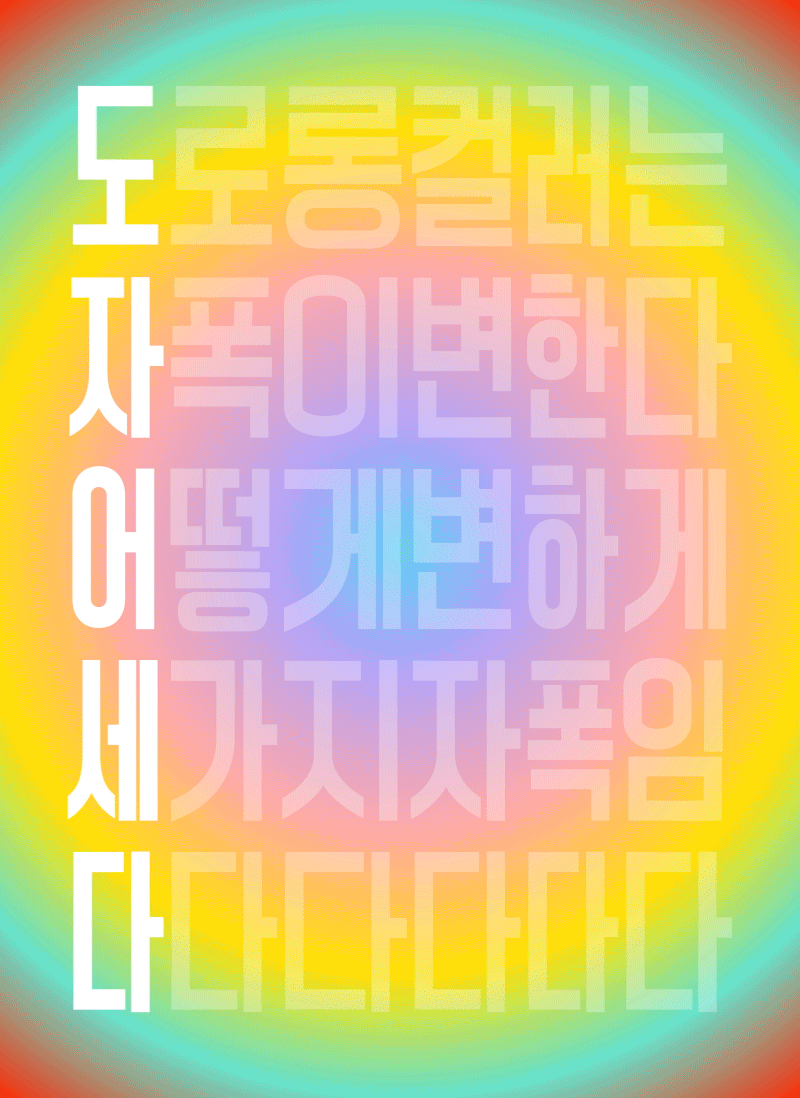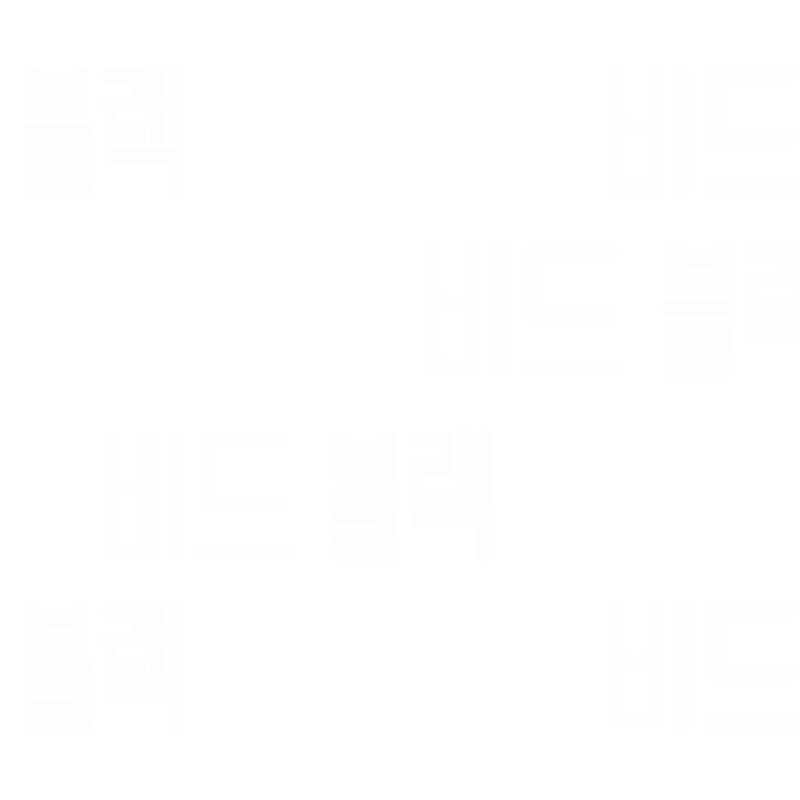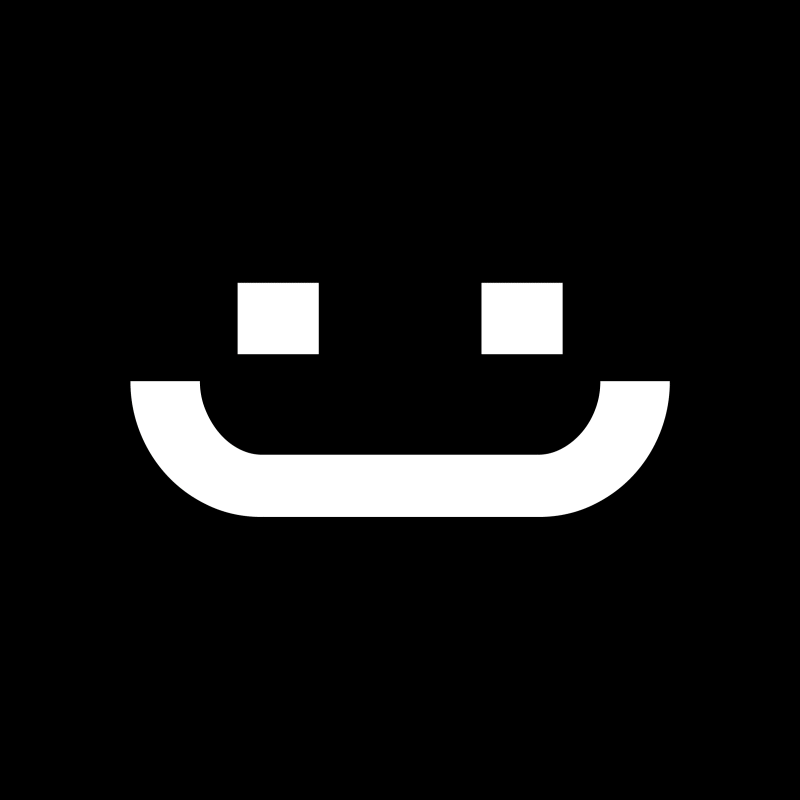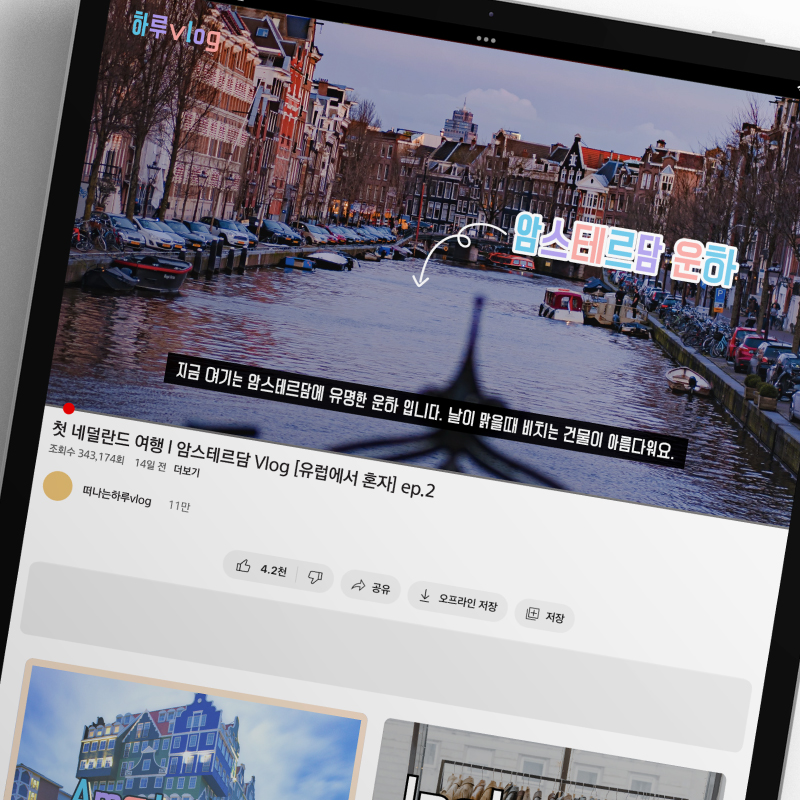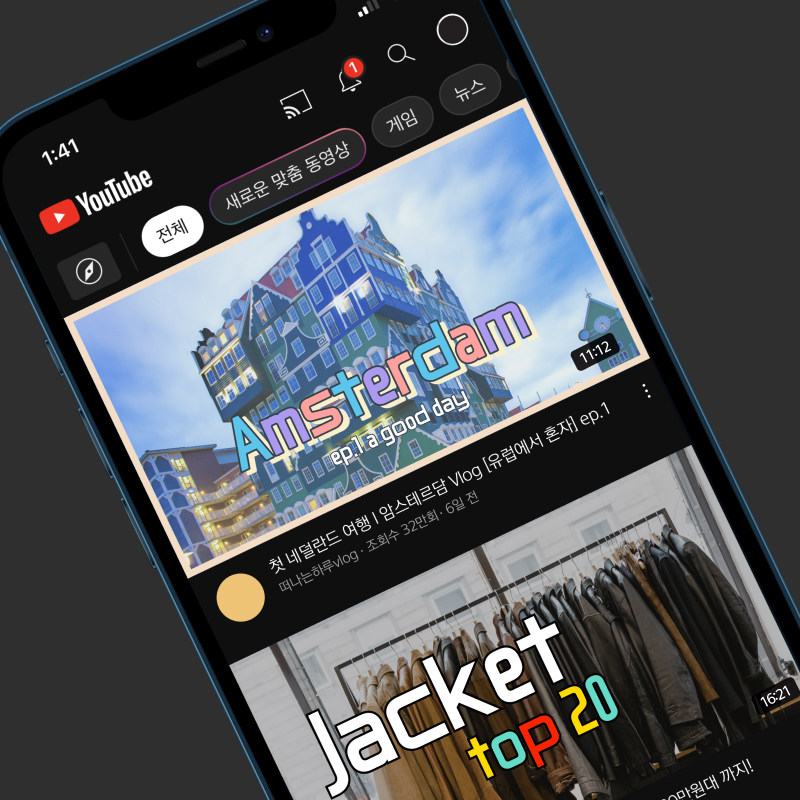
RixDororong-Color
3 Style - Black, Vivid, PastelRix도로롱 서체를 기반으로 제작된 도로롱 시리즈의 컬러폰트입니다.
컨셉에 따라 활용하기 좋은 Black, Vivid, Pastel 3가지 컬러 조합이 포함되어 있습니다.
순서대로 글자 폭이 다르게 적용되어 재미 요소를 느낄 수 있는 서체입니다.